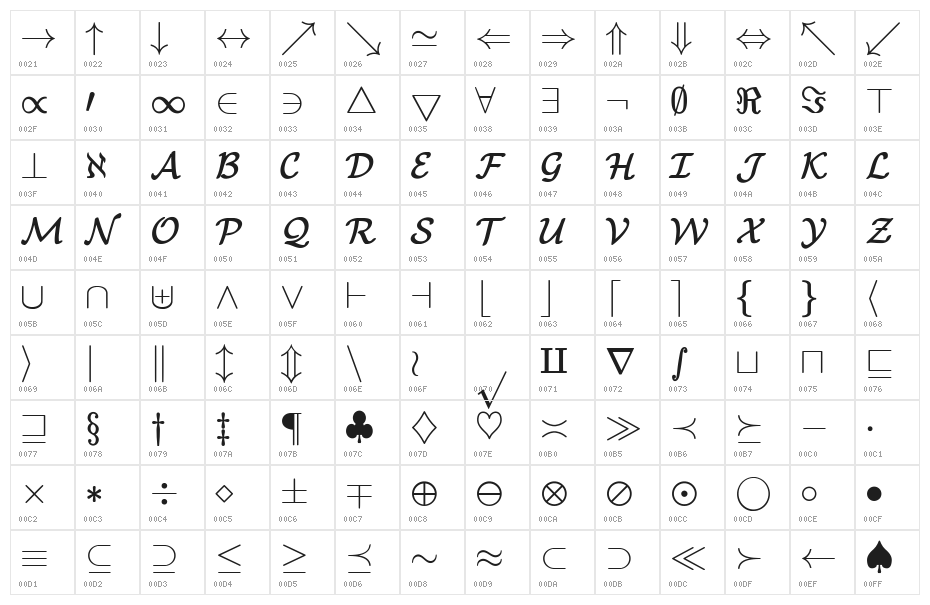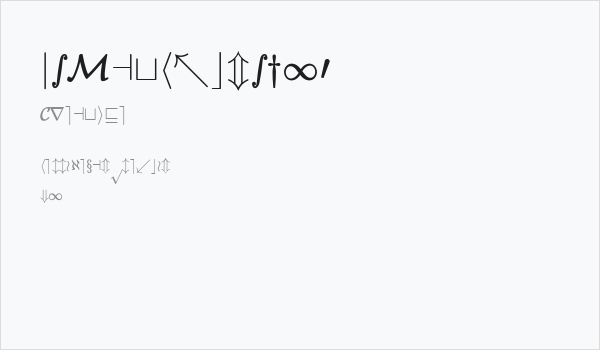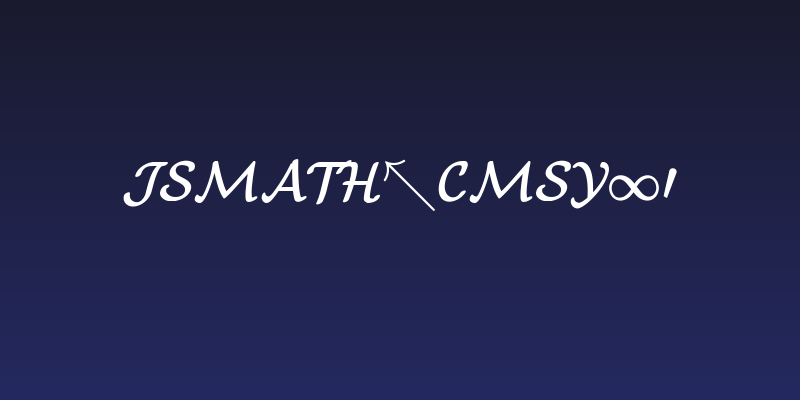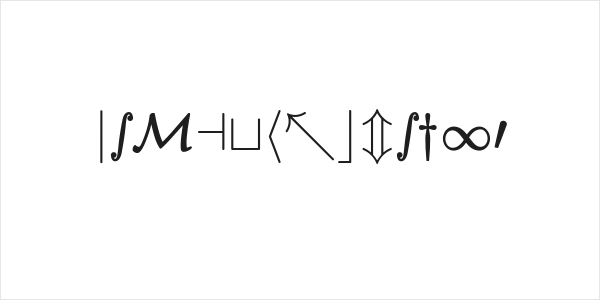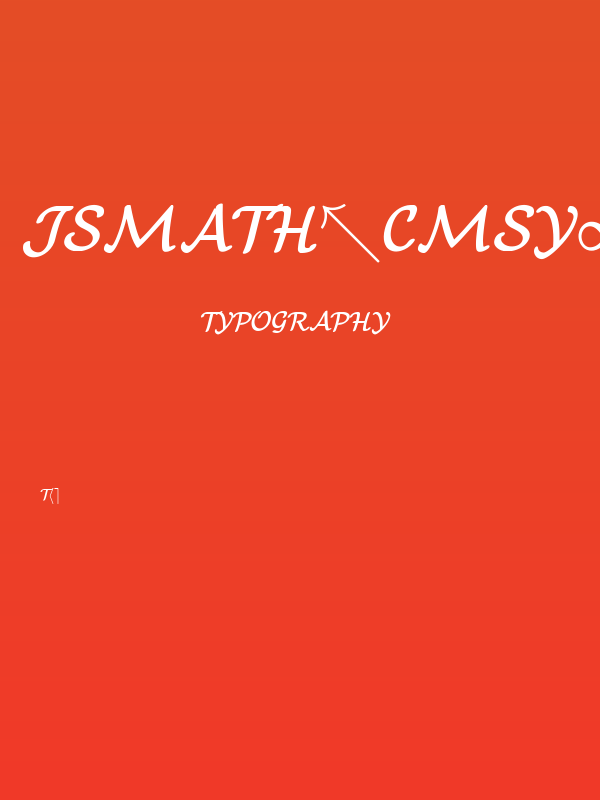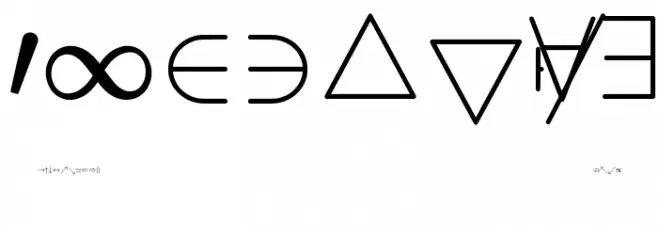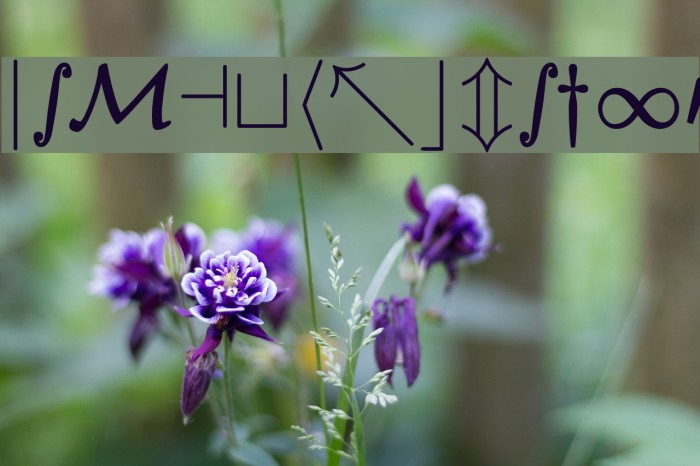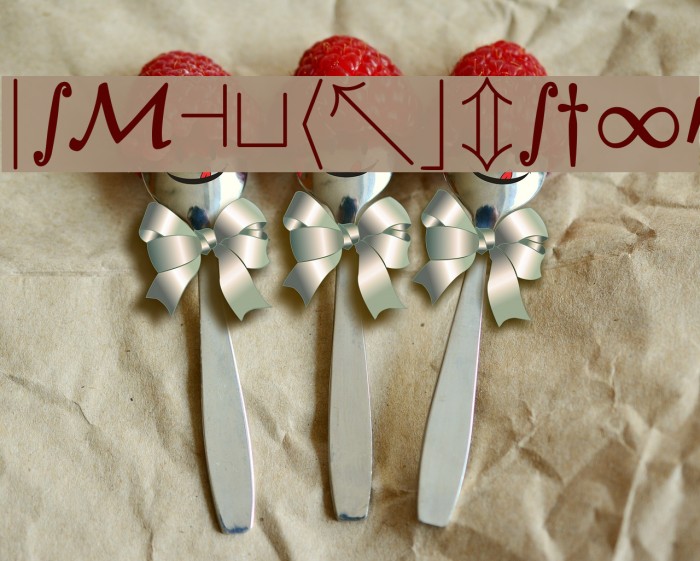
jsMath-cmsy10 Font
| 用途 | Technical documents, educational materials, academic papers. |
| おすすめプロジェクト | Ideal for academic papers, technical documents, and educational materials requiring mathematical notation. |